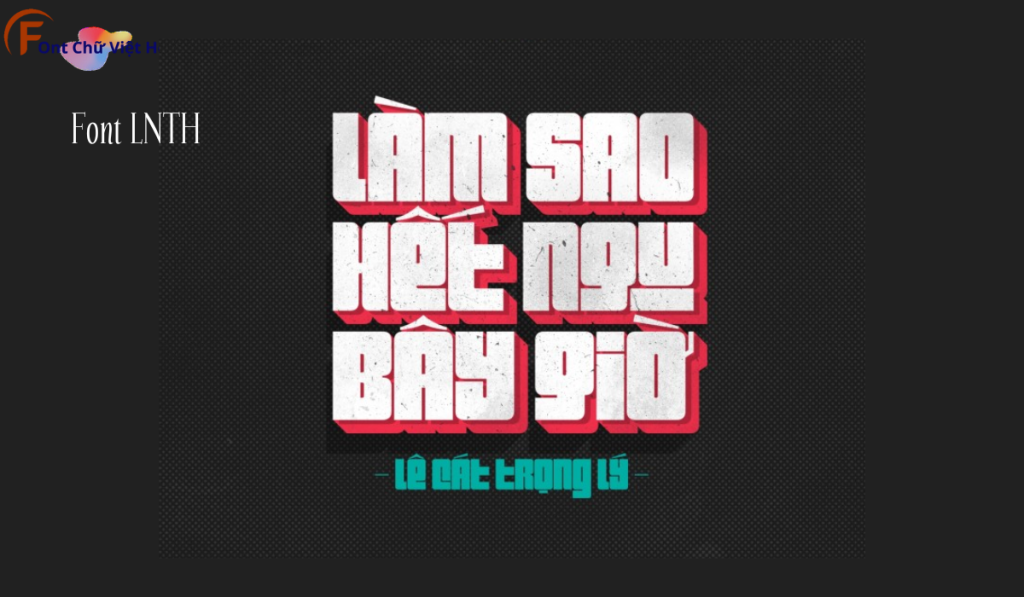
Font LNTH Pincoya Black Việt Hóa
Tác giả: LNTH
Độ dày: Thường
Font LNTH Pincoya Black Việt Hóa là một font chữ mạnh mẽ, thuộc bộ LNTH, với thiết kế đậm và nổi bật. Phong cách của font này phù hợp với các dự án thiết kế cần sự mạnh mẽ và thu hút, như poster, tiêu đề, hoặc bảng hiệu quảng cáo. Font LNTH Pincoya Black Việt Hóa mang đến sự nổi bật và dễ nhận diện, ứng dụng trong các lĩnh vực sáng tạo. Đặc điểm hình dạng của font bao gồm các đường nét dày và chắc chắn, giúp tăng tính thẩm mỹ và sự chú ý. Việc Việt hóa font giúp người dùng dễ dàng sử dụng trong các thiết kế tiếng Việt, mang lại sự tiện lợi và linh hoạt.